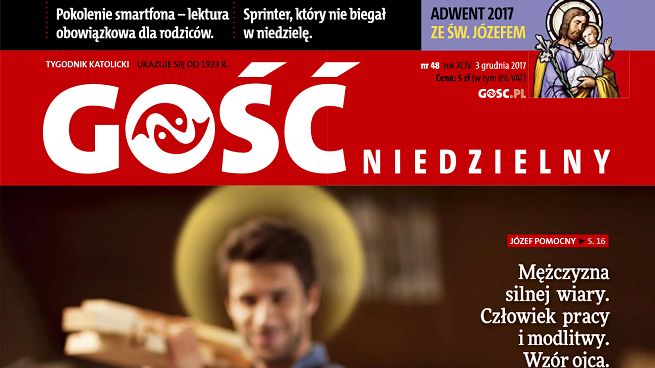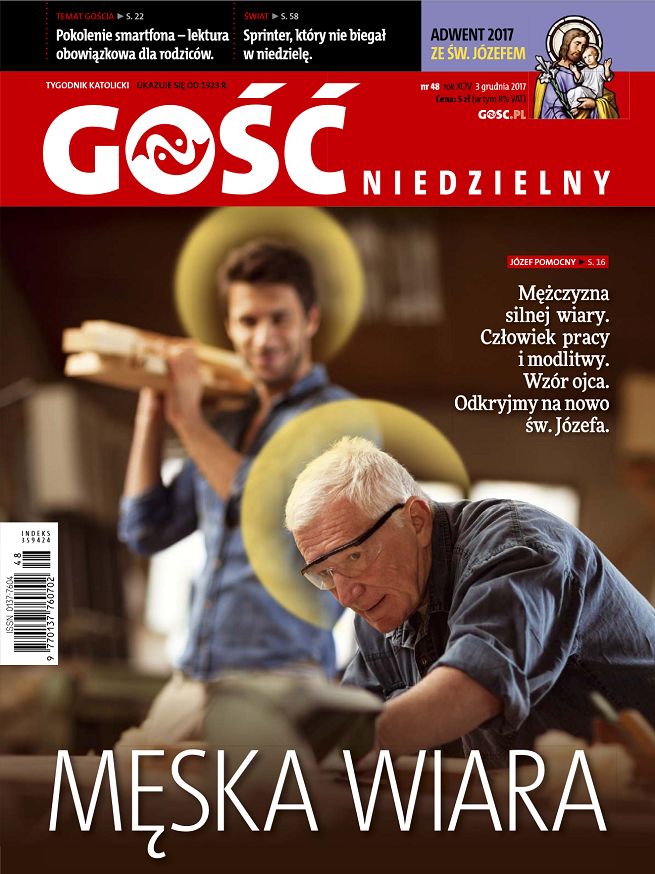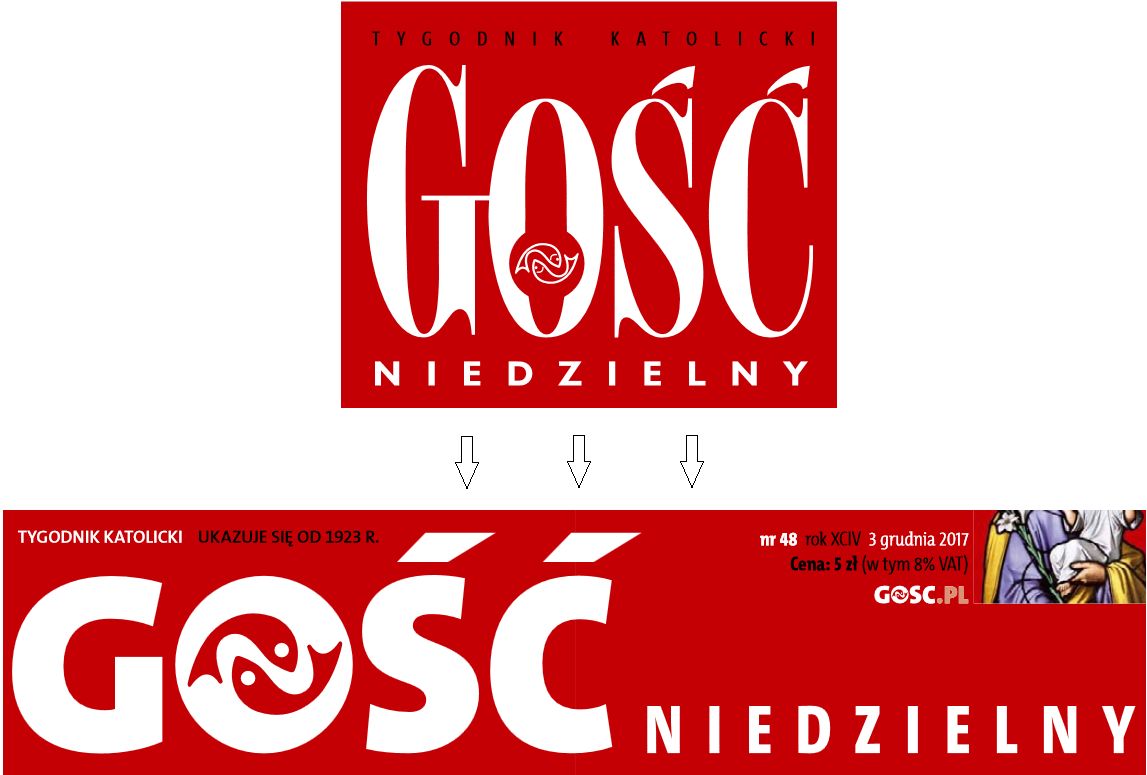
„Gość Niedzielny” z nowym logo, czcionką i papierem. „Mały lifting”
Tygodnik „Gość Niedzielny” (Instytut Gość Niedzielny) zmieniło swój logotyp i winietę, a także czcionkę i typ papieru. - To mały lifting - podsumowuje ks. Marek Gancarczyk, redaktor naczelny pisma.
Nowe logo „Gościa Niedzielnego” tak jak poprzednie ma biało-czerwoną kolorystykę. Zmieniła się natomiast czcionka i układ nazwy pisma, znacznie powiększono symbol dwóch ryb w literze „o” oraz dodano informację, że pismo ukazuje się od 1923 roku.
Analogicznie zmieniło się logo serwisu internetowego Gosc.pl
Ksiądz Marek Gancarczyk, redaktor naczelny „Gościa Niedzielnego”, we wstępniaku w nowym numerze określi te zmiany jako mały lifting. - Każdy kiedyś musi iść do fryzjera. Jak Szanowni Czytelnicy zauważyli, zmieniło się logo, program telewizyjny stał się integralną częścią pisma, a czcionka i rodzaj papieru ułatwią czytanie - opisał.